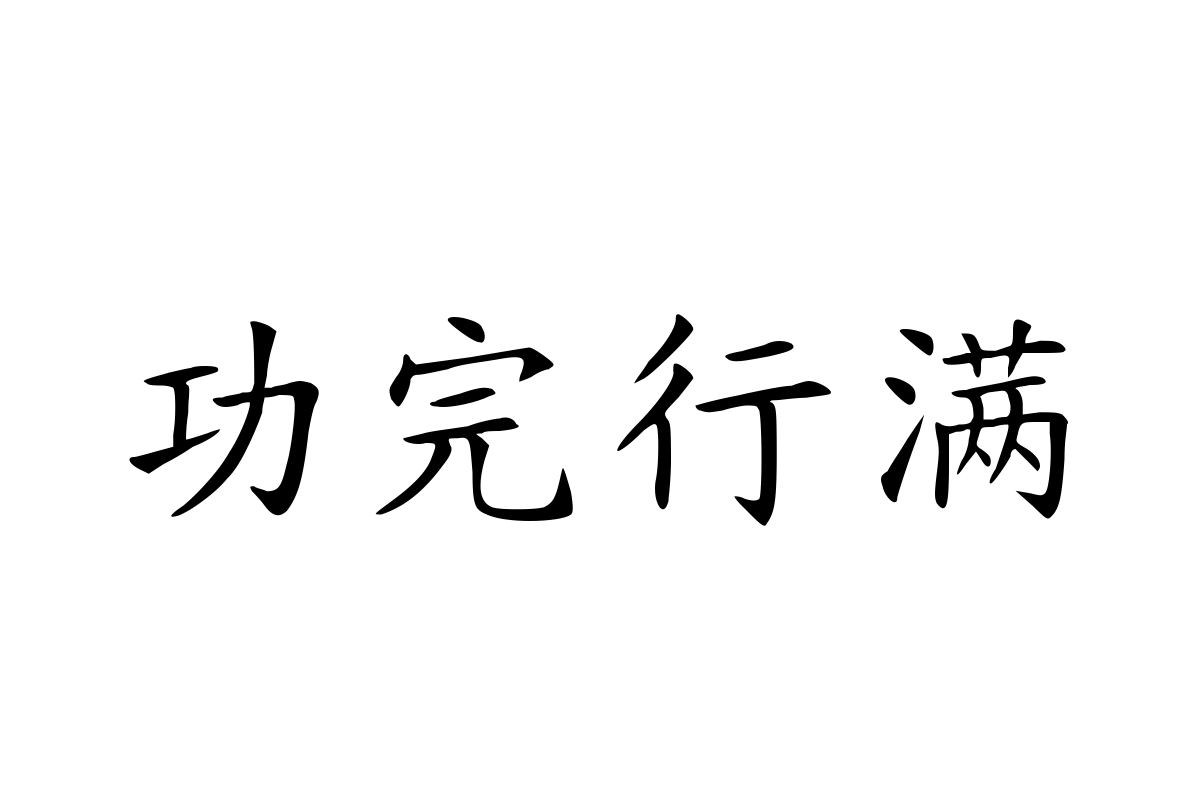
三极楷书简字体是一种具有独特风格的汉字书写风格,它的特点是笔画粗细变化明显,线条流畅有力。这种字体在古代书法艺术中有着重要的地位,被誉为“天下第一行书”。
三极楷书简字体的特点主要体现在以下几个方面:
1. 笔画粗细变化明显:在书写过程中,每个字的笔画粗细都有较大的变化,使得整个字体看起来既有力度又有美感。
2. 线条流畅有力:由于笔画粗细的变化,使得整个字体的线条流畅有力,给人一种强烈的视觉冲击力。
3. 结构紧凑:三极楷书简字体的结构紧凑,每个字都紧密相连,没有多余的空间,使得整个字体看起来更加整齐划一。
4. 易于识别:由于笔画粗细变化和线条流畅有力的特点,使得三极楷书简字体具有较高的辨识度,便于读者阅读和理解。
总之,三极楷书简字体以其独特的风格和特点,在古代书法艺术中占有重要地位,被后人广泛研究和传承。